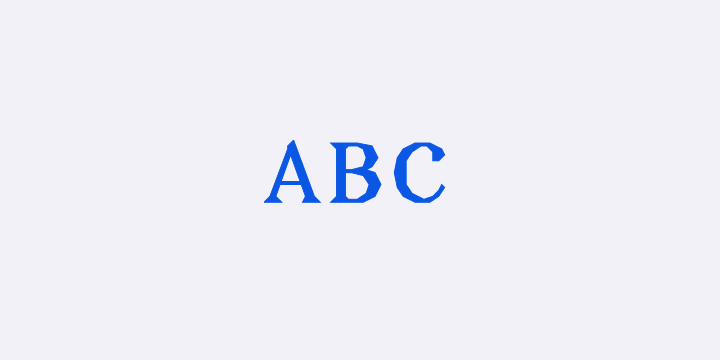
关于Avara-Bold字体字库信息
字体全名: Avara-Bold
设计师: Raphaël Bastide
字体简介: Avara 是一个自由过渡衬线无曲线字体系列。其节点的放置完全基于粗糙的方形网格。这种设计选择的最初原因是为了促进字体的协作,现在它导致了这个字体系列的激进和高度受限的形状。它由 Raphaël Bastide 于 2011 年 11 月启动并首次发布;从那时起它一直在更新,最后在这里发布。将来可能会再次更新,tho。也许由你。 Bold风格由 Raphaël Bastide 发起,并由 Wei Huang 和 Lucas Le Bihan 延续;Lucas Le Bihan 的 Bold Italic;Black 由 Walid Bouchouchi 和 Jérémy Landes 发起,然后再次加粗并由 Lucas Le Bihan 完成。